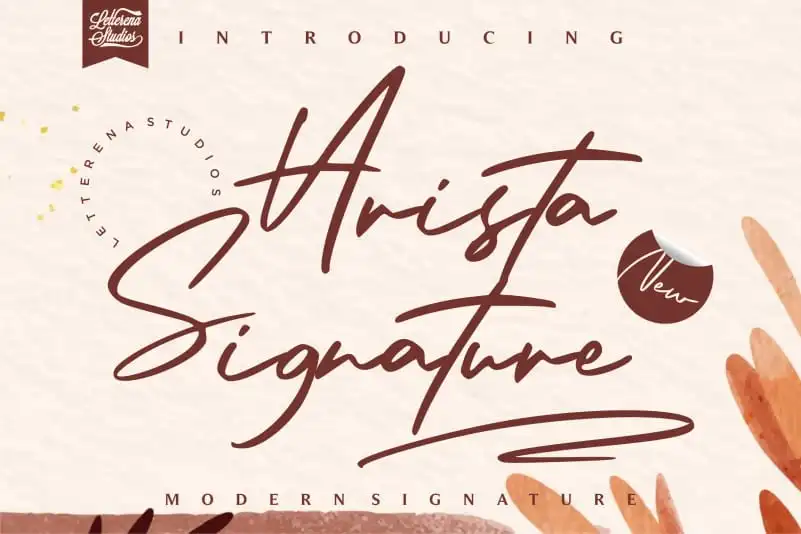
Arista Signature Font – Download Grátis
Arista Signature é uma fonte escrita à mão desenvolvida por Letterenastudios que oferece uma sensação acolhedora e natural para qualquer projeto de design. Com linhas leves e um acabamento autêntico, esta fonte é perfeita para textos pessoais e emotivos. Seu uso exclusivo pessoal sem fins comerciais permite que você desfrute da verdadeira essência desta grife. A Aristas Signature é ideal para anotações de notas, recados emocionantes ou qualquer outro projeto onde você deseja capturar o sentimento genuíno através das palavras escritas à mão. Não importa qual seja seu objetivo com esta fonte, ela certamente será um complemento inspirador e único.